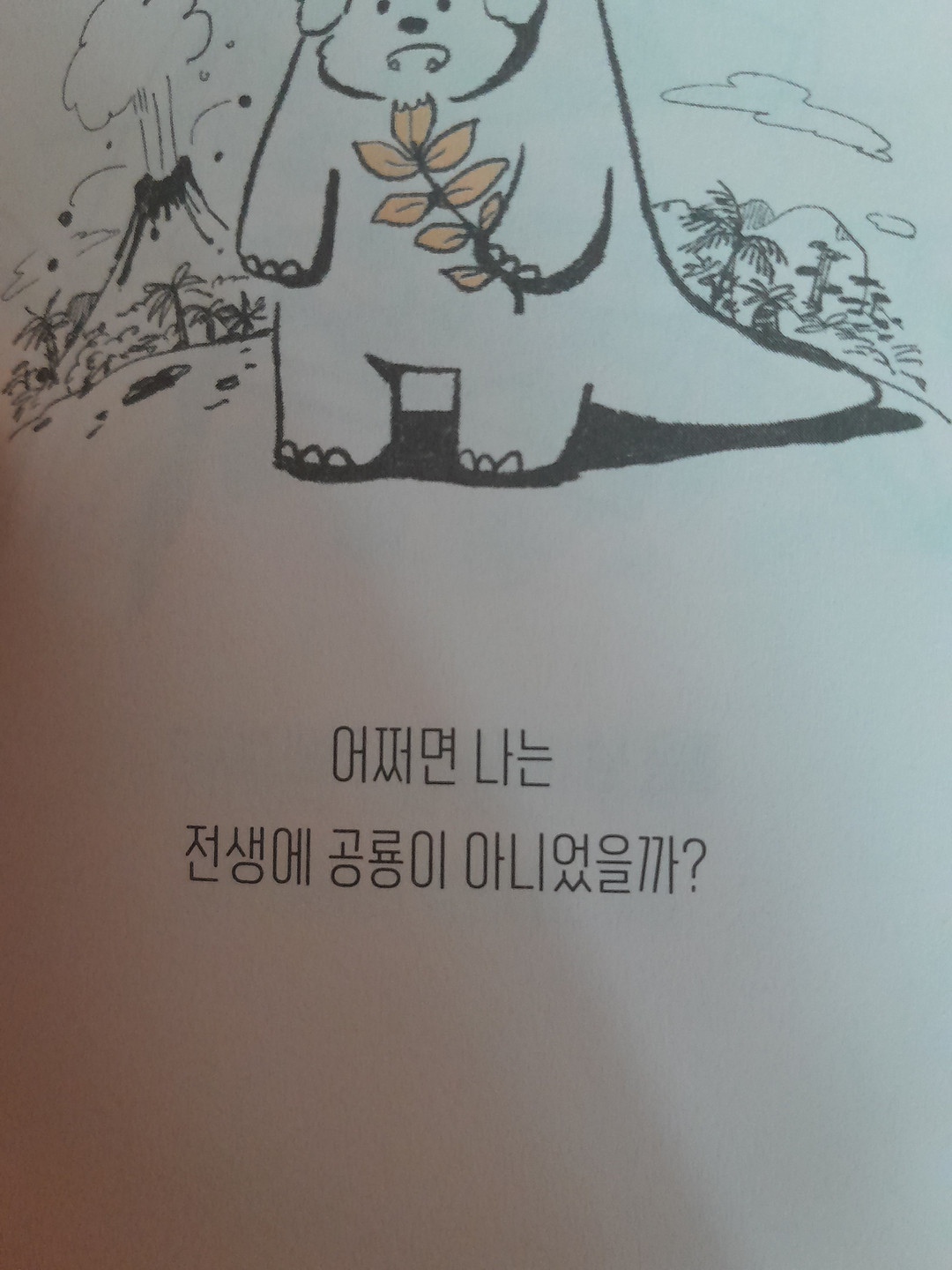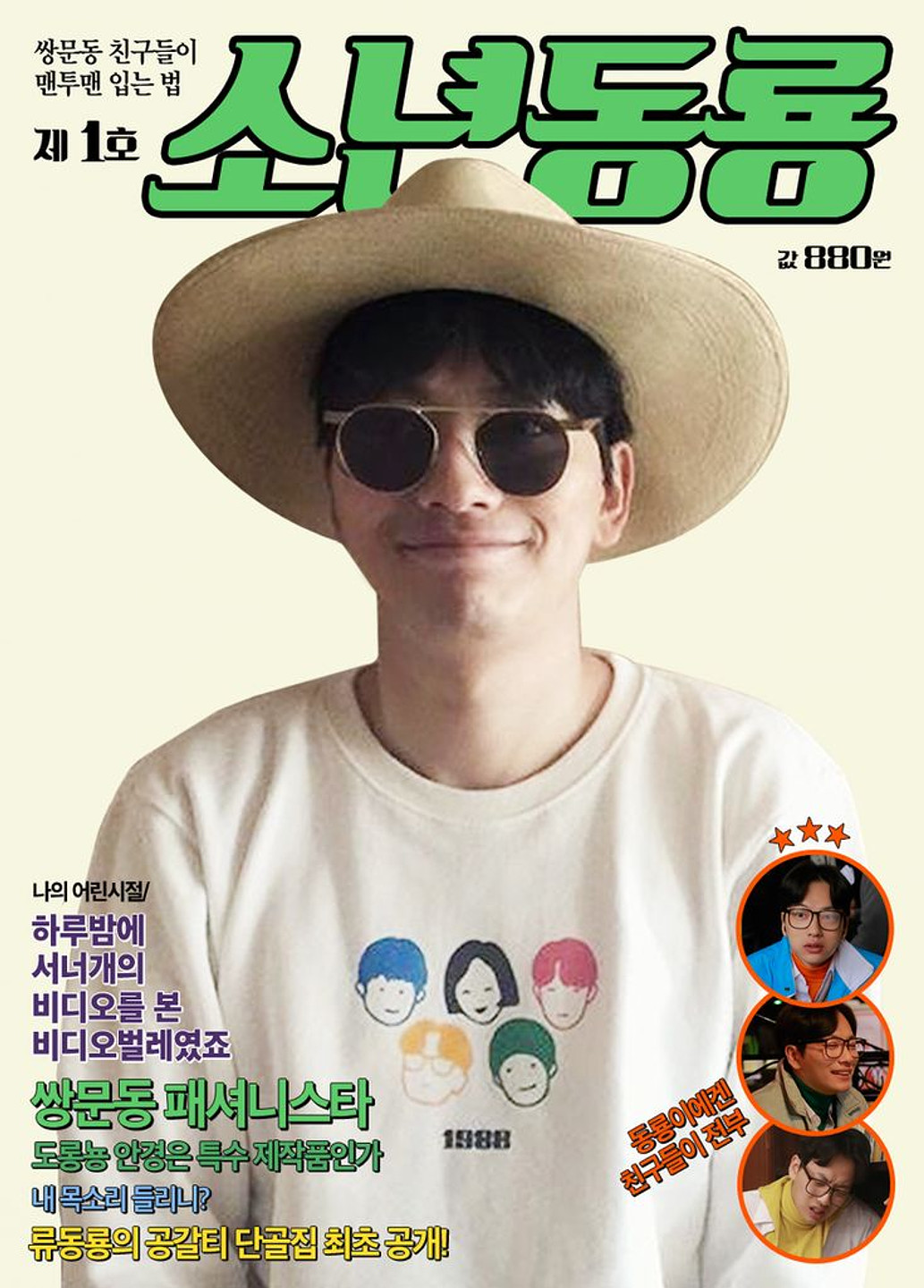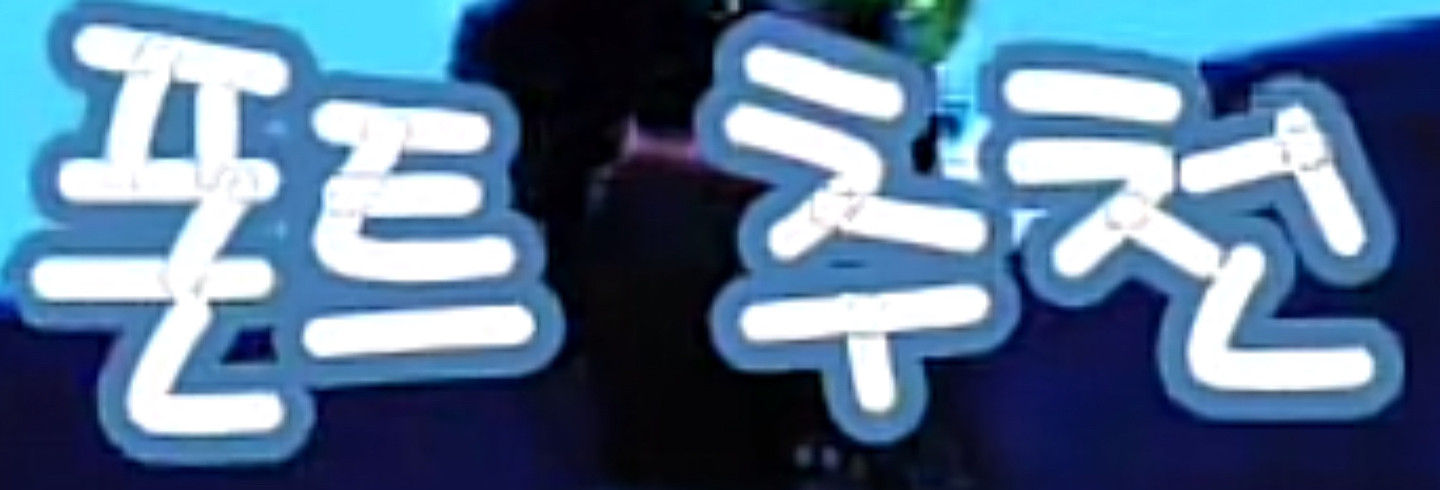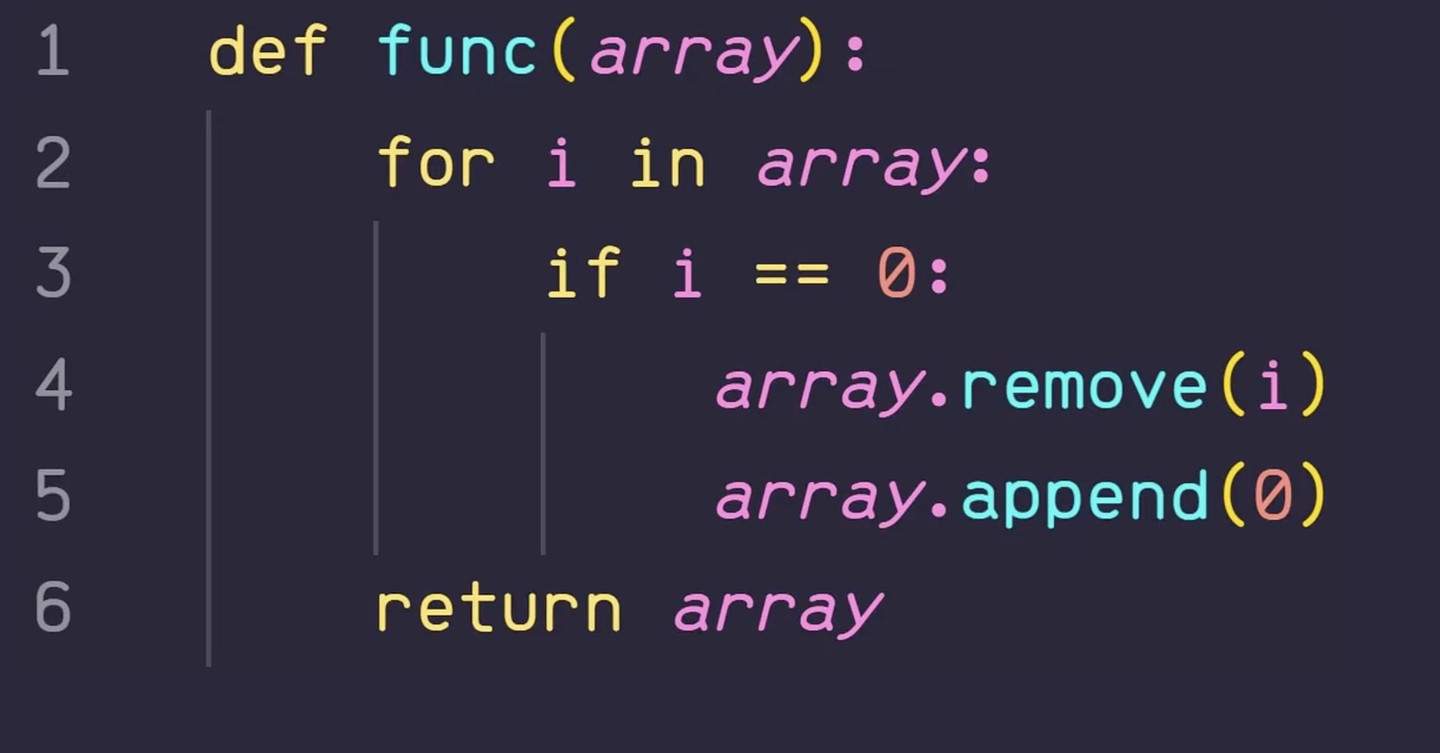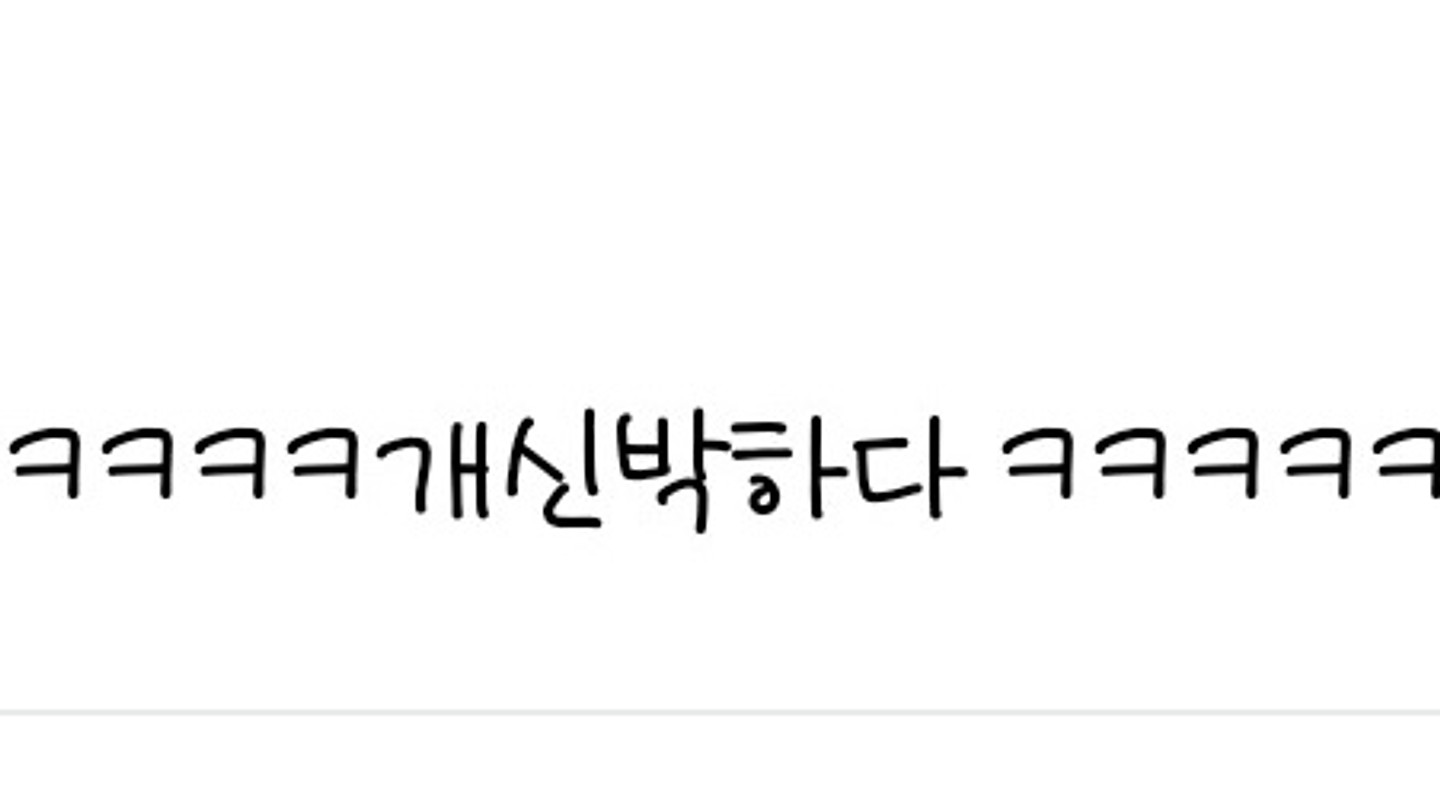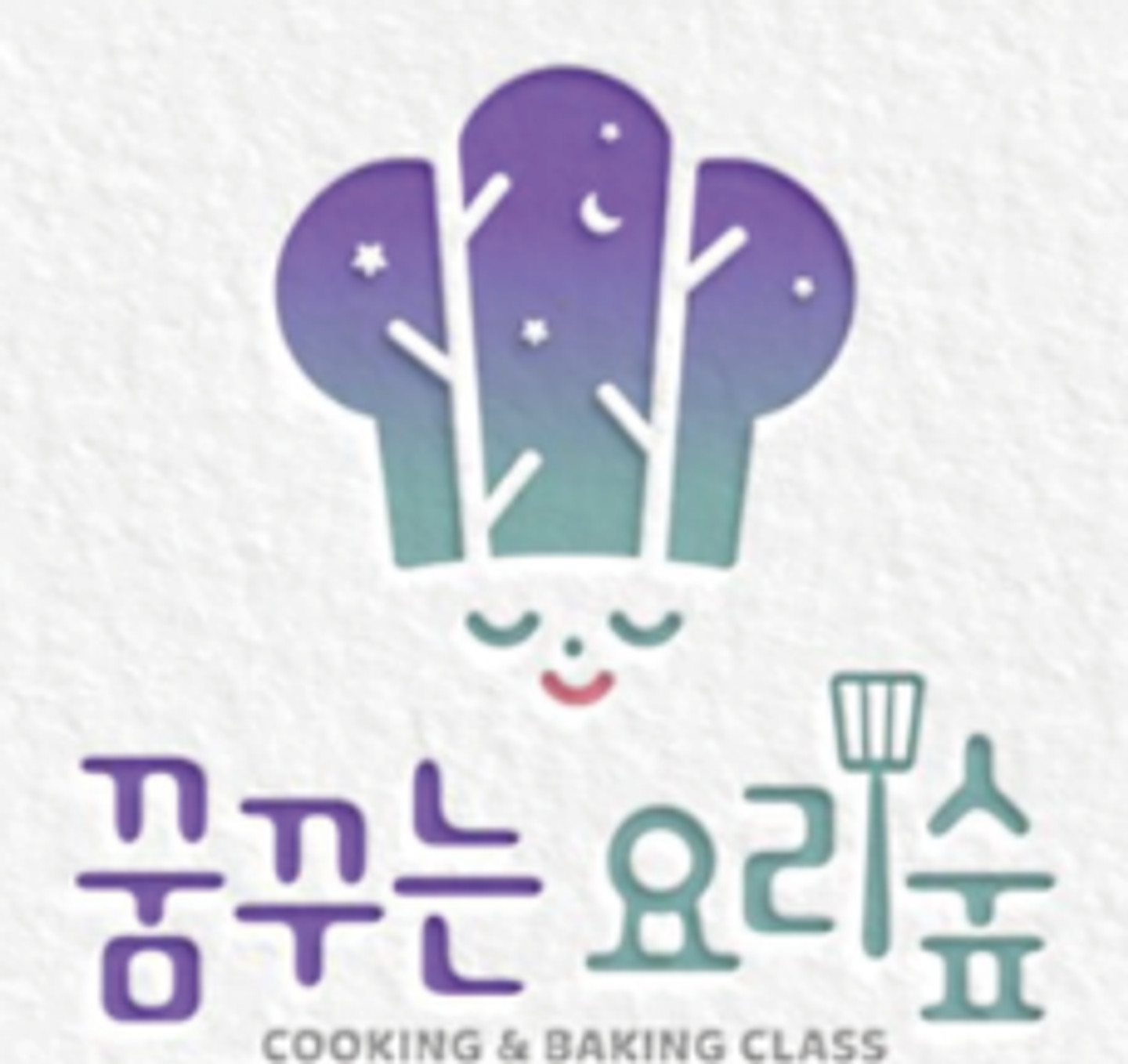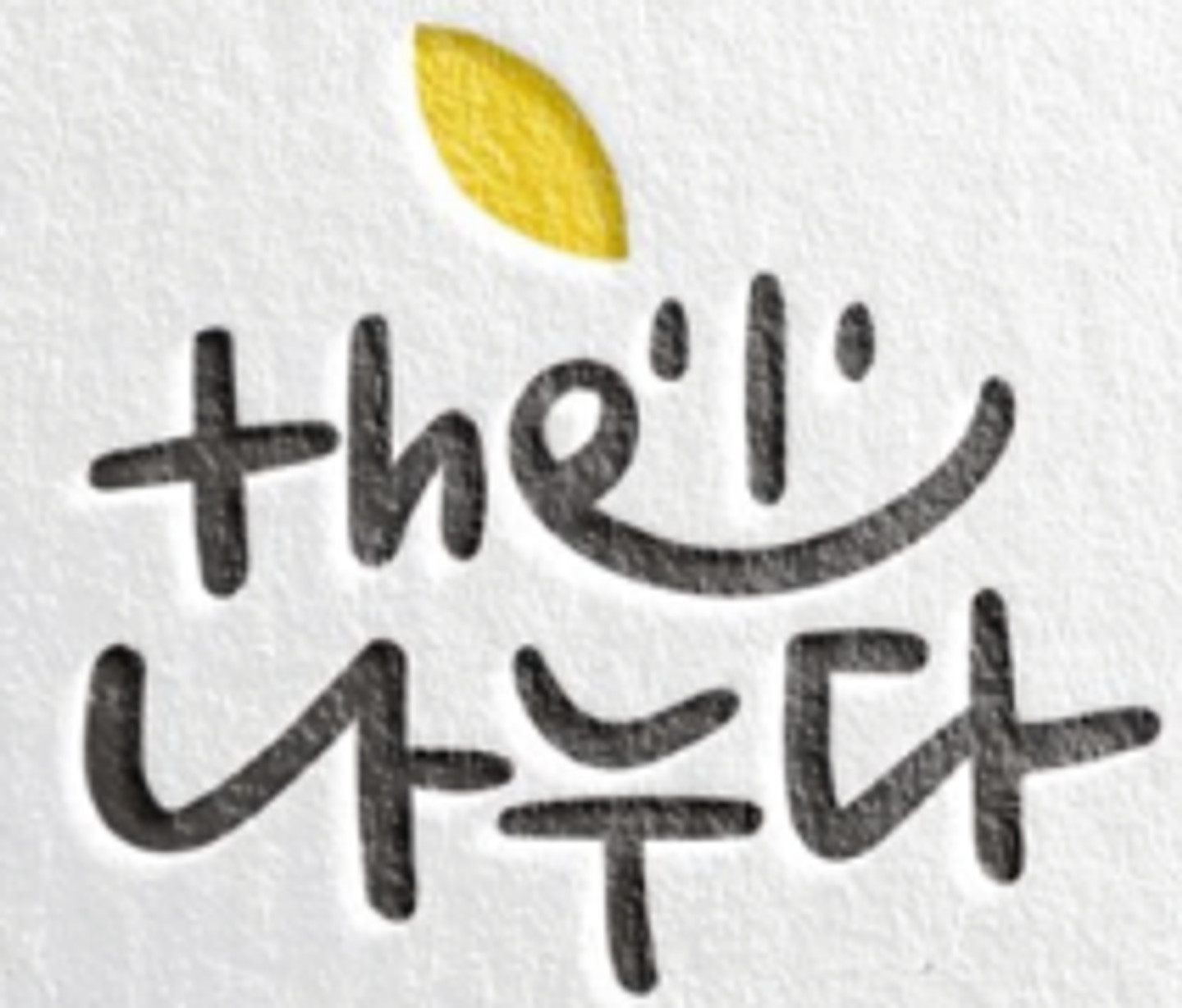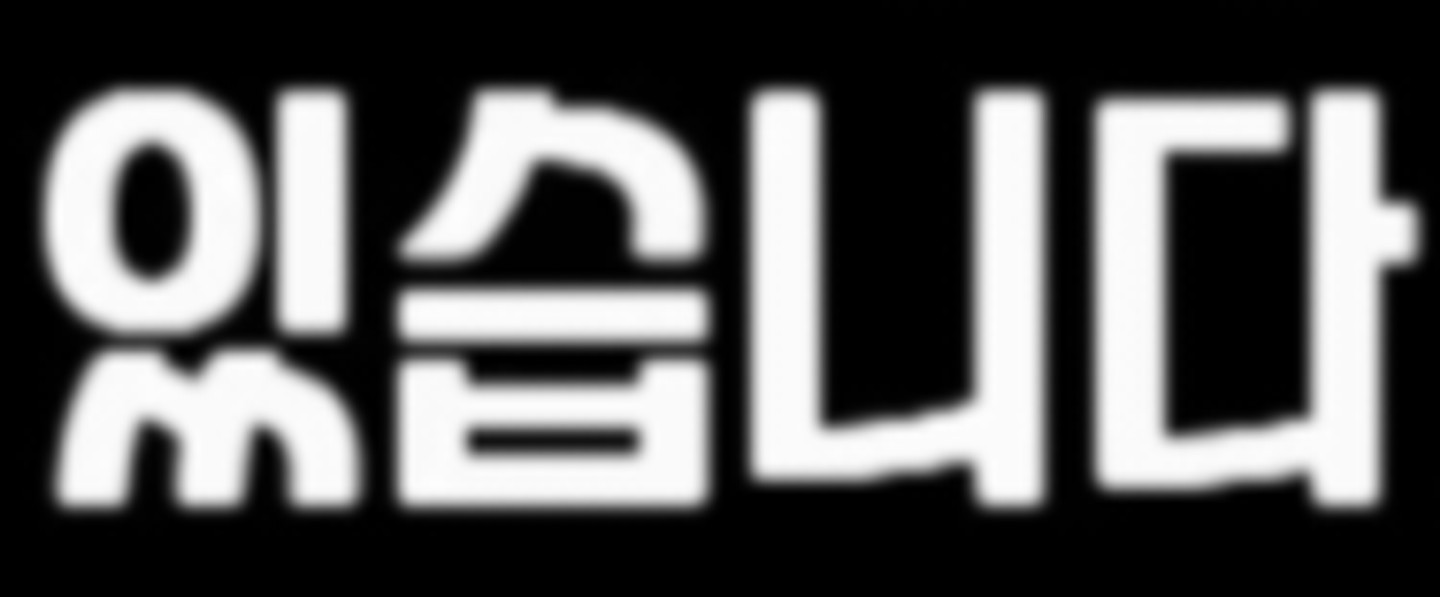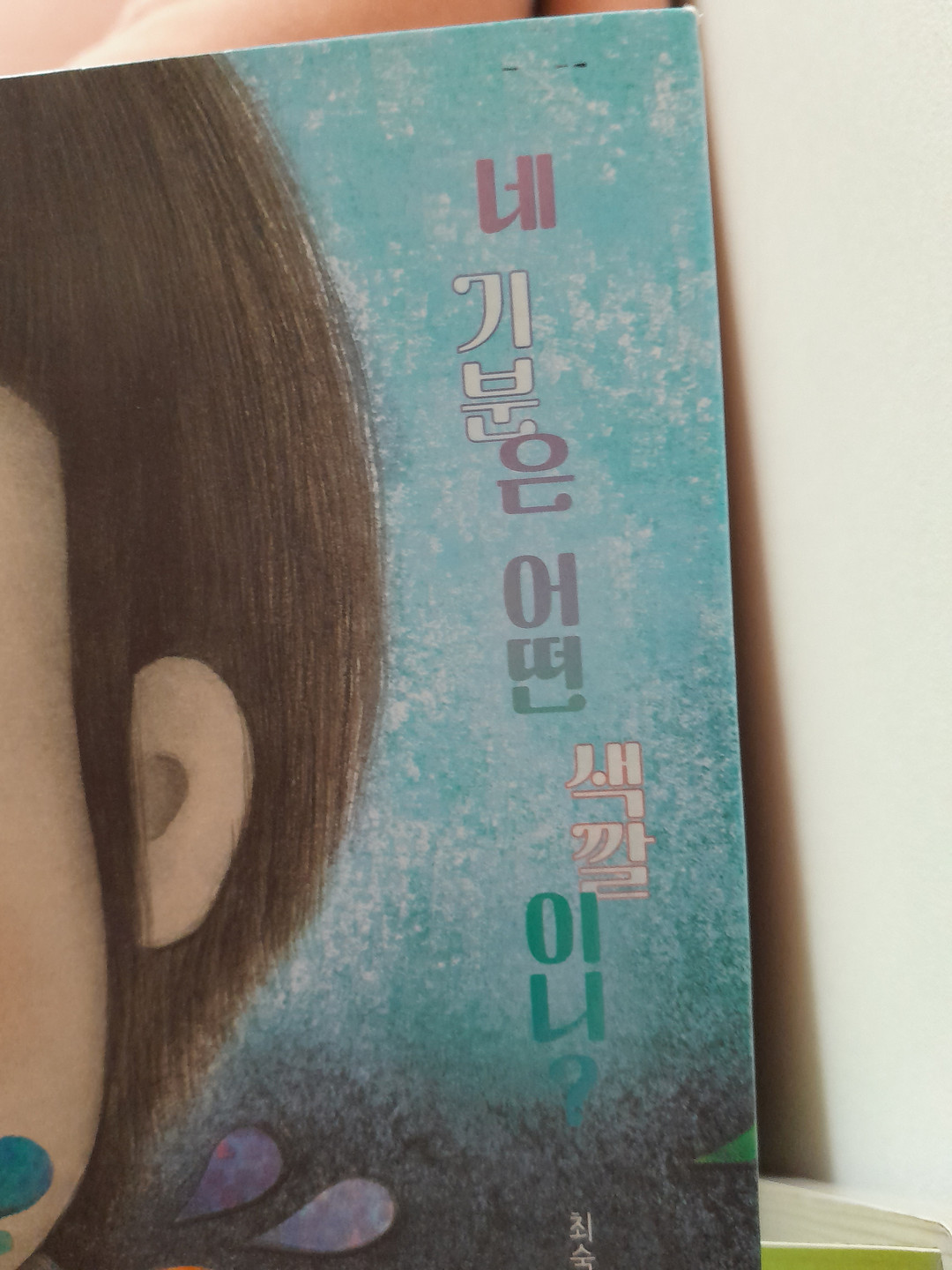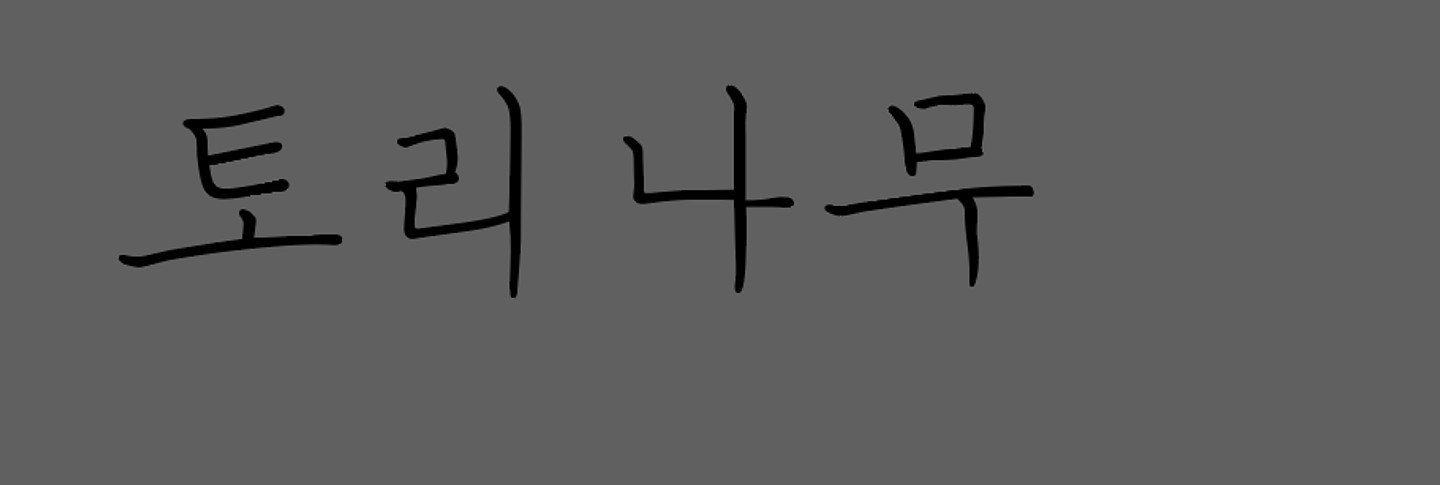
인스타 릴스에서 찾았어요
이 폰트 무엇인가요?
이 돋움체 폰트 이름 뭔가요? 출처는 찰스엔터 유튜브 입니다! https://youtu.be/v1v9jc4tXs8?si=weB51qt15jHPveNN
이 폰트 무슨 폰트인지 알 수 있을까요???
좌측위에 09:22 시간 폰트 정보 알고싶습니다 !!🙏🙏
민홍님 브이로그 자막 속 이 폰트 뭔가요 ?! 도와주세요 🥹
무슨 폰트인가요 ~?
이거 영문 무슨 폰트인가요ㅜㅜ 정말 궁금해요!! 알려주세요ㅜㅜ
요거 무슨 폰트일까요..?
이건 어떤 폰트인가요?
여기 글씨체 무슨 폰트일까요?
수성혜정체 비슷한데 ㅊ이 좀 다른 거 같아요... 돌에 새긴 건데 뭔지 아시는 분 계실까요?
정말정말 궁금합니다
궁금합니다!!
저기 숫자 폰트 뭔지 아시는 분 있나요?
폰트 이름이 궁금합니다!!!
혹시 이 글씨체 무슨 글씨체인지 알 수 있을까요..??
'추석 선물세트 기획전' 폰트 어떤건지 알 수 잇을까요??
이 폰트도 궁금합니다 동글동글~ 비슷한거라도 알려주시면 참고하고 싶어요
변형한건지 폰트가 궁금합니다
Pretty Please
무슨 폰트인지 아시는 분...?
폰트체알고싶어요
각각 어떤 폰트인지 알 수 있을까요?
무슨폰트?
이거 무슨 폰트인지 알수 있을까요 ㅠㅠ
무슨 폰트인지 알 수 있을까요 ㅠ
서체가 너무 궁금해요ㅠㅜ 너무 본 서체인데 기억이...
맨 앞에 '도' 를 보시면 ㄷ이 위아래로 좀 긴거같은데 글씨체를 알 수 있을까요? 따옴표는 아예 다른 글씨체 같습니다.
이거 무슨 폰트일까요 비슷한 무료 폰트라도 궁금합니다
아이브 영상에 나오는 이 폰트는 뭔가요? 커오히같긴한데 또 다른것같아서요
"건강한 내 삶을 지켜줄" 이랑 "건강프렌즈" 각각 글씨체 알려주세요!!
무슨 폰트인지 궁금해요!! 고수님들 도와주세요🥹
무슨 글씨체인지 궁금합니다 !!
폰트좀 찾아주세여ㅠㅠㅠ
폰트 알려주세여ㅠㅠ
이서체는 어떤걸까요..? 아시는분 답변부탁드립니다.
해당 글꼴 어떤걸까용
글씨체 궁금해요
무슨 폰트인지 알수있을까요?
두꺼운 손글씨? 폰트 무슨 폰트일까요
'저편의 미래에서'와 '대전시립미술관' 폰트 알려주세요
무슨 폰트인지 알수있을까요? 부탁드립니다~~
어썸 스테이지에 온 엔플라잉 이거 어떤 폰트인가요? ㅠㅠ
하단 분홍칸 폰트 문의드립니다!
이거 무슨폰트일가요ㅠ
혹시 이거 무슨 폰트인지 알수있을까요?ㅠㅠ
김도영 글자 폰트 궁금해요!
ㅈ과ㅊ 모양이 포인트인 저 폰트 너무 궁금해요..
글씨체 궁금해요ㅠ
눈누 구경하다가 제가 찾는 폰트와 비슷해서 궁금해서 끌올 해봅니다! 사진에 사용된 폰트 뭘까요?!? 너무 궁금합니다
사진에 사용된 돋움체가 뭔지 궁금합니다 돋움체랑 돋움체는 다 찾아봤는데 비슷한 느낌이 안나네요 https://blog.naver.com/weareparang/223649646724 이 사이트에 사용된 폰트입니다
이 글씨체 뭘까요?
폰트에 대해서 설명해주세요
무슨 글자일까요?
이 한자 폰트 이름이 어떻게되지요?